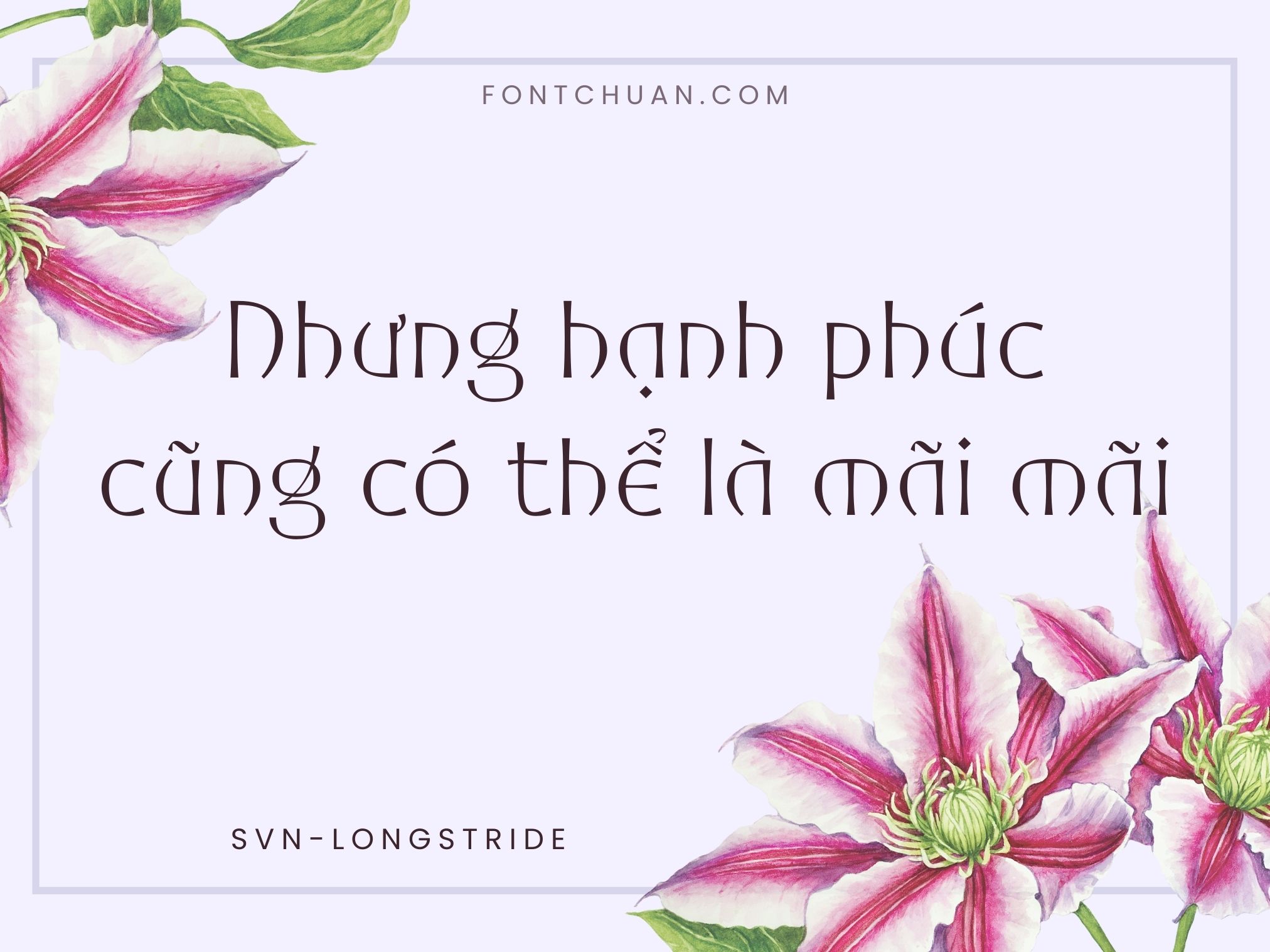
Font SVN Longstride là phiên bản Việt hóa của kiểu chữ Longstride, được thực hiện bởi STYLEno.1 Fonts. Đây là một Font Serif lấy cảm hứng từ các chữ cái La Mã cổ điển, mang đến sự kết hợp giữa nét cổ điển và hiện đại. Font này bao gồm đầy đủ các ký tự chữ hoa, chữ thường, chữ số và dấu câu, hỗ trợ đa ngôn ngữ. Ngoài ra, Longstride còn cung cấp các ligature và ký tự thay thế, giúp tăng tính linh hoạt và sáng tạo trong thiết kế. Font này phù hợp cho nhiều mục đích sử dụng như thiết kế logo, tiêu đề, bao bì sản phẩm và các ấn phẩm truyền thông.
SVN Longstride lý tưởng cho các dự án thiết kế yêu cầu sự trang trọng và cổ điển, như thiết kế logo thương hiệu, tiêu đề tạp chí, bao bì sản phẩm và các ấn phẩm truyền thông. Các ngành nghề như quảng cáo, giáo dục và công nghệ có thể tận dụng font này để tạo điểm nhấn trong thiết kế. Ngoài ra, font cũng thích hợp cho các sự kiện như Tết, Giáng sinh, Valentine và các lễ hội khác.